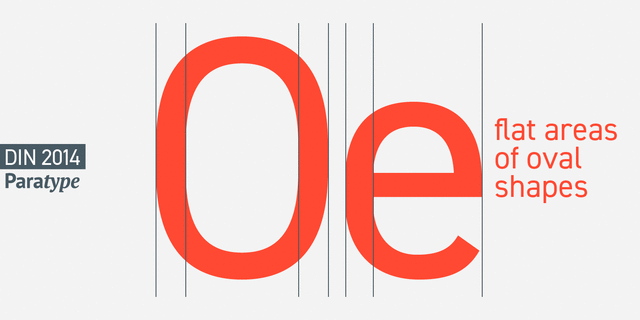
Опис гарнітури DIN 2014 — современная интерпретация известного шрифта DIN. Начертание Regular вполне пригодно для набора достаточно длинного текста, а светлые и жирные вариации особенно хорошо работают в крупном кегле. Гарнитура включает 18 начертаний: шесть прямых и шесть курсивов нормальной ширины, а также шесть зауженных начертаний. Шрифт разработан Василием Бирюковым и выпущен компанией ПараТайп в 2015 году.